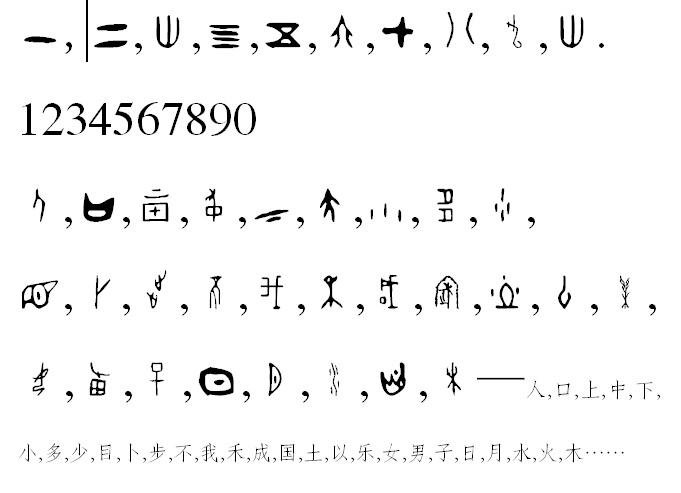
甲骨文字體
甲骨文字體免費(fèi)版是一款非常獨(dú)具個(gè)性的甲骨文字體,有一種濃烈的復(fù)古感,讓文字可以回到過(guò)去,非常的別致,歡迎喜愛(ài)的朋友到綠色資源網(wǎng)下載體驗(yàn)!
甲骨文字體是目前中文字體中最古老的字體,該字體的出現(xiàn)標(biāo)志著人類(lèi)社會(huì)進(jìn)入文明時(shí)代,可用于包裝印刷、平面廣告、繪畫(huà)藝術(shù)、創(chuàng)意設(shè)計(jì)等應(yīng)用,現(xiàn)在綠色資源網(wǎng)小編在這里為網(wǎng)友提供免費(fèi)下載。